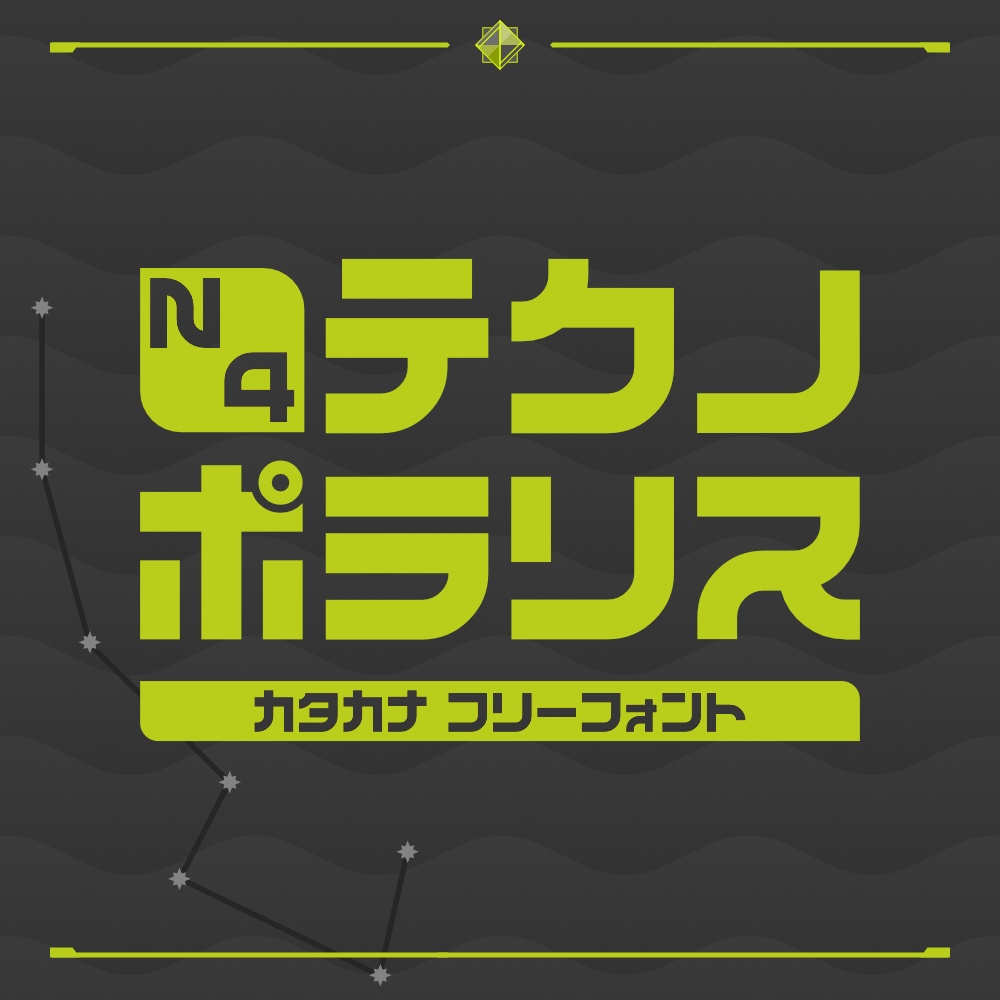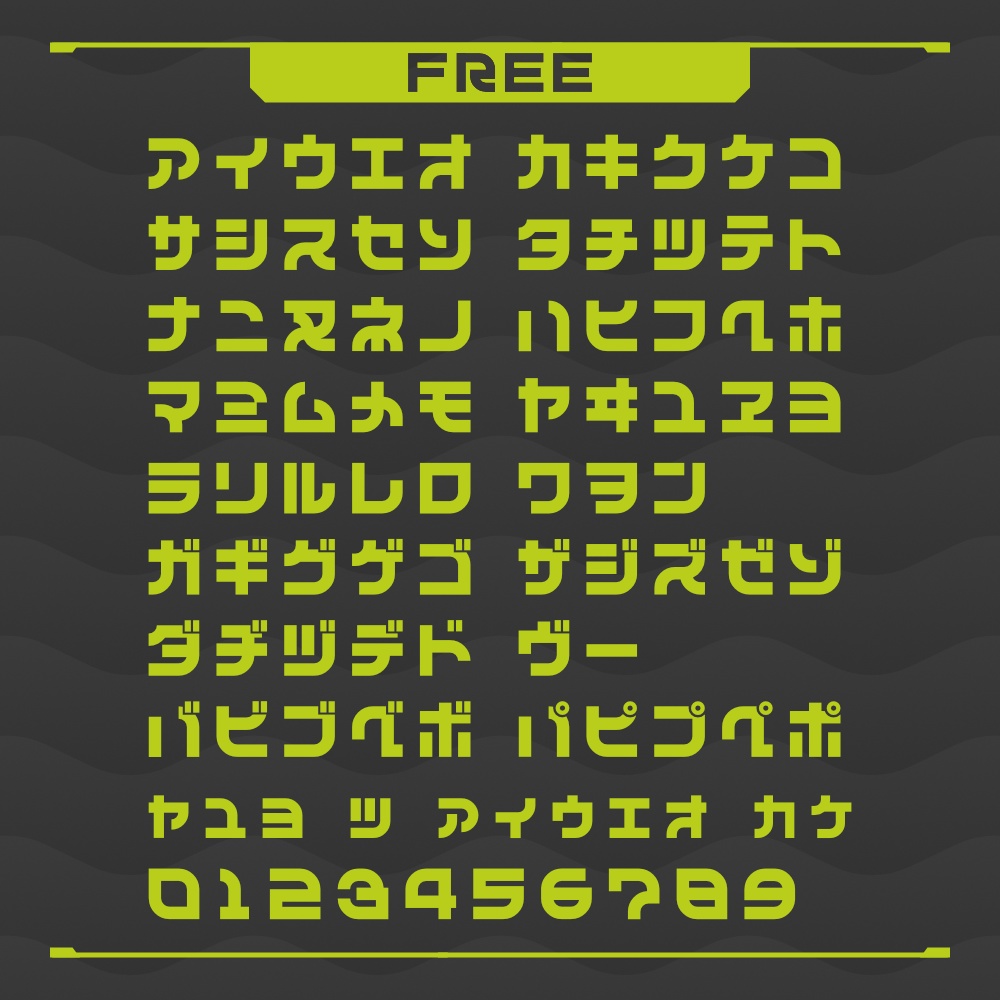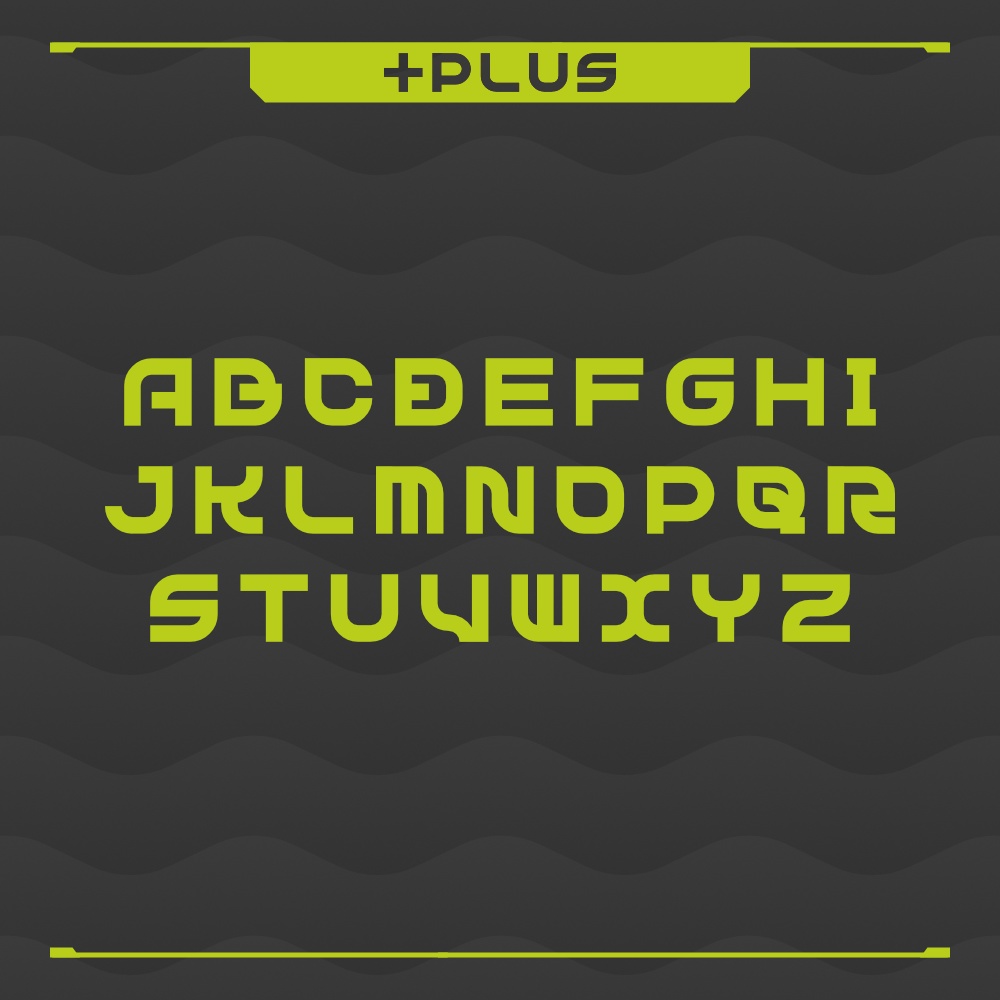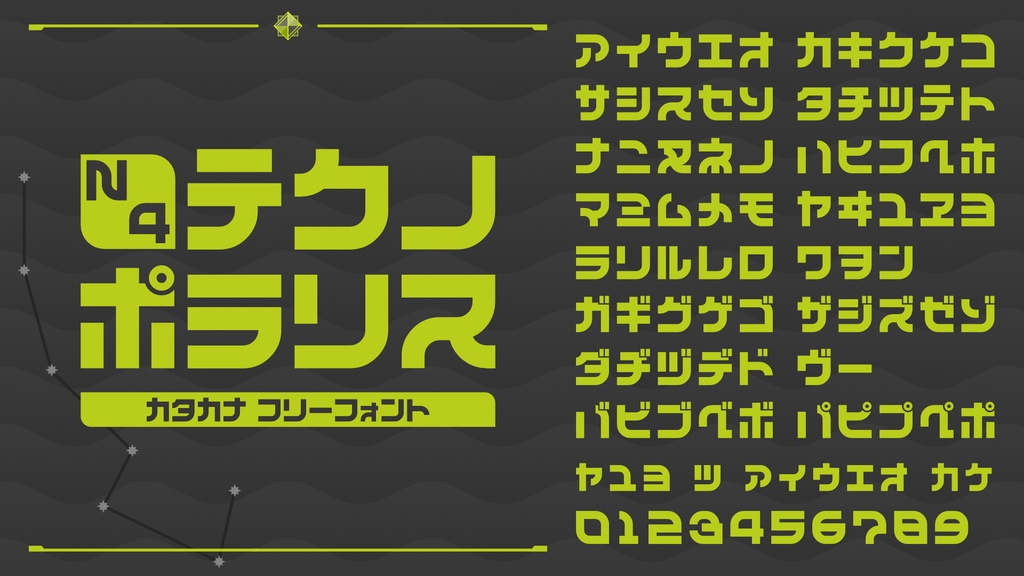
N4テクノポラリス【フリーフォント】無料/商用可
カタカナフォント『N4テクノポラリス』
"直線"と"うなり"のカタカナフォント
インパクトある太字のカタカナフォント 有償バージョンでは追加で大文字アルファベットも収録! 2バージョンともに商用利用可能で使えます。 えらべる2バージョン [ FREE:¥0 ] 基本のカタカナと数字、一部記号を収録 [ PLUS:¥500 ] FREEの内容に加えて、大文字アルファベットを収録 支援して頂ける方向け